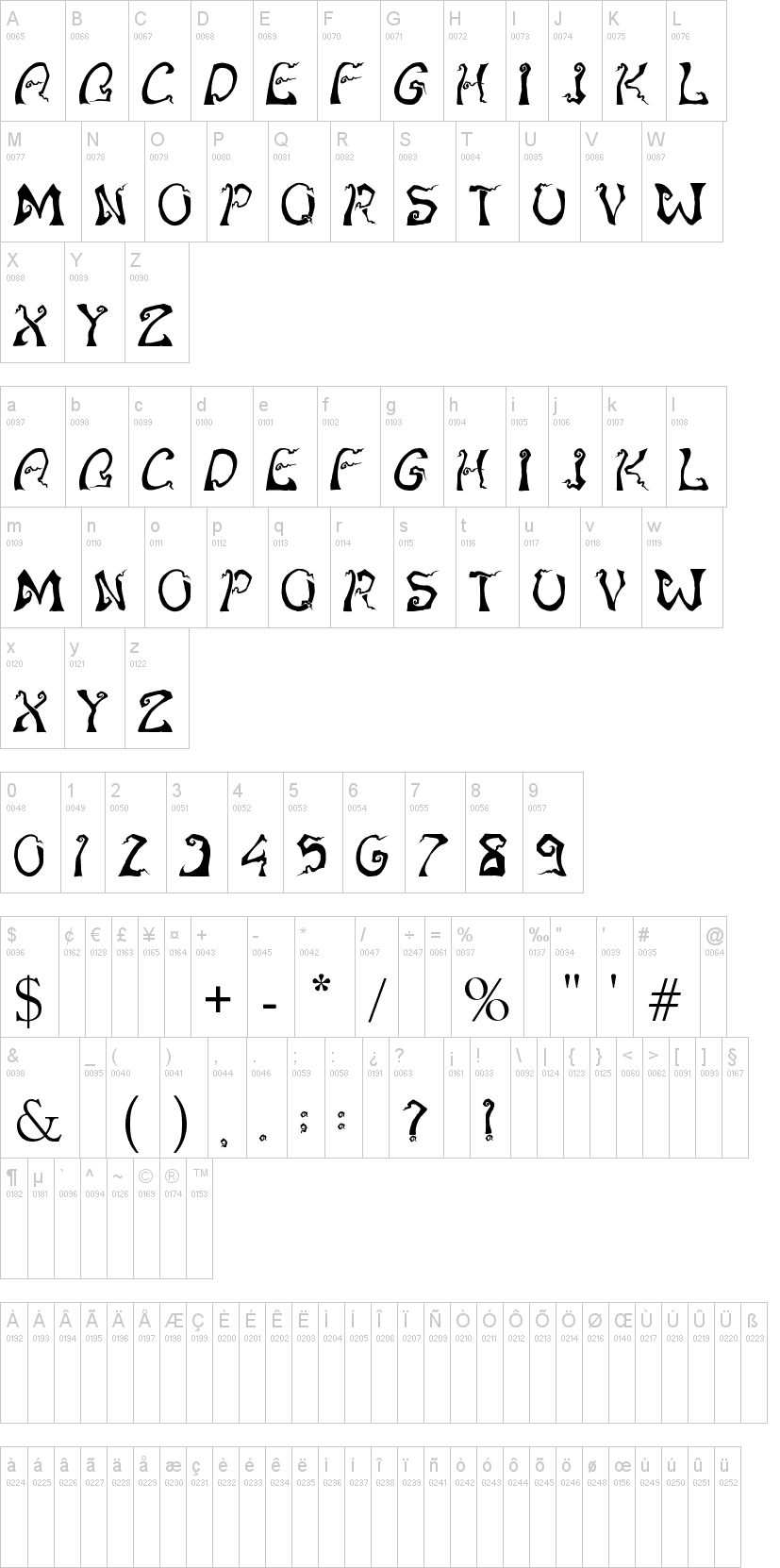
Stranglethorn
Stranglethorn 是一种免费的手写风格字体,它受到了非洲和拉丁美洲文化的启发。这款字体由美国设计师 Nick's Fonts 设计,它的特点是不规则的线条和弯曲的形状,使其看起来更加有机和自然。 Stranglethorn 字体具有一定的艺术气息,适合用于海报、标志、书籍封面等设计中。此外,它还包含多个字形和标点符号,可以满足不同的设计需求。
Stranglethorn是一款非常不错的手写艺术字体,具有很好的视觉感,适合于文化类的宣传设计、商业类品牌的广告和产品包装设计以及个性化文字排版等较多场景。